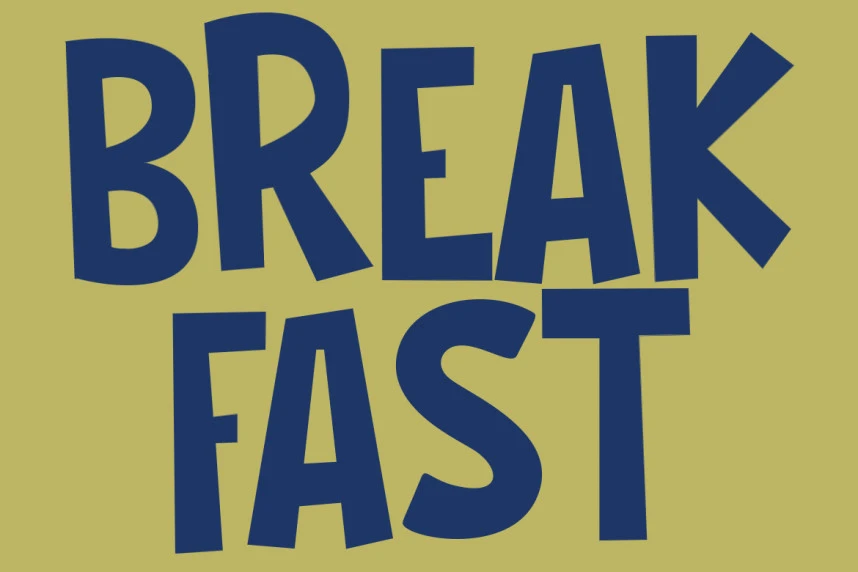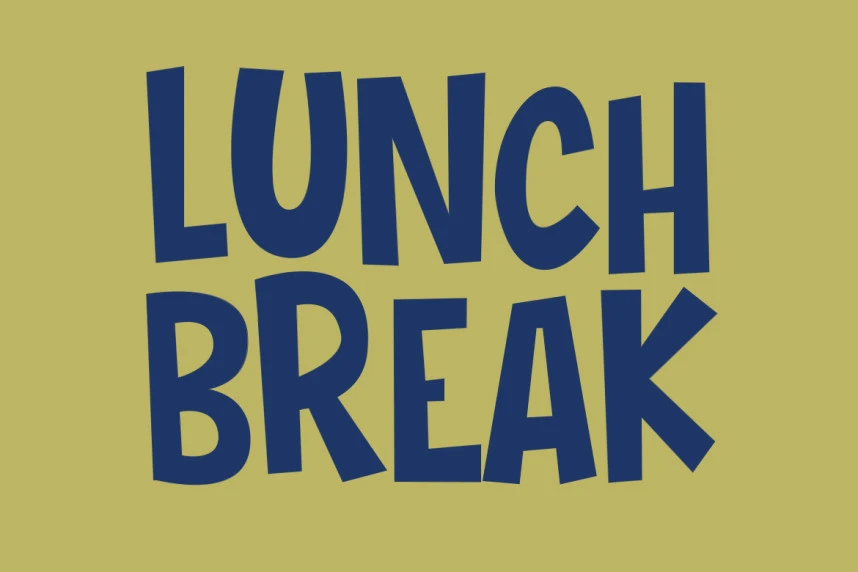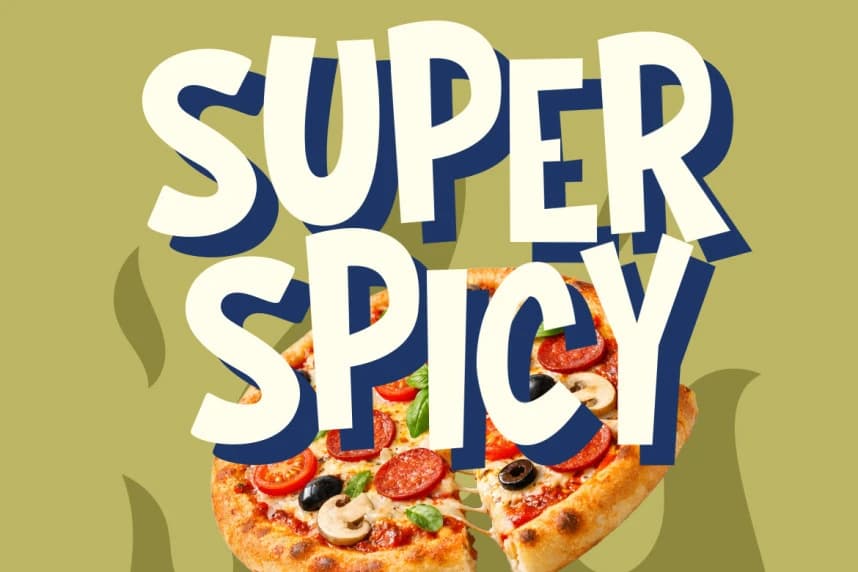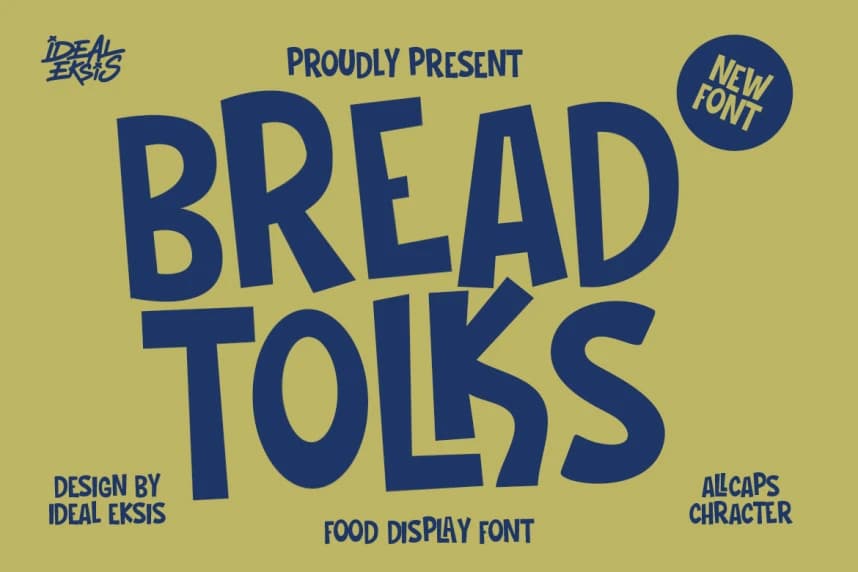
Bread Tolks Font
Bread Tolks Font - Bu kalın gösteri yazı tipi, kalın, elle çizilmiş harf biçimlerine sahip, oyunbaz ve enerjik bir karakter sunar. Çizgiler kalın ve düzensizdir; her harfe benzersiz, organik bir şekil vererek onu erişilebilir ve dostane kılar.
Bread Tolks Font - Bu kalın gösterim yazı tipinde kalın ve elle çizilmiş harf biçimlerine sahip, oyuncu ve enerjik bir karaktere sahiptir. Çizgiler kalın ve düzensizdir; her karaktere benzersiz, organik bir şekil vererek erişilebilir ve arkadaşça bir his sağlar.